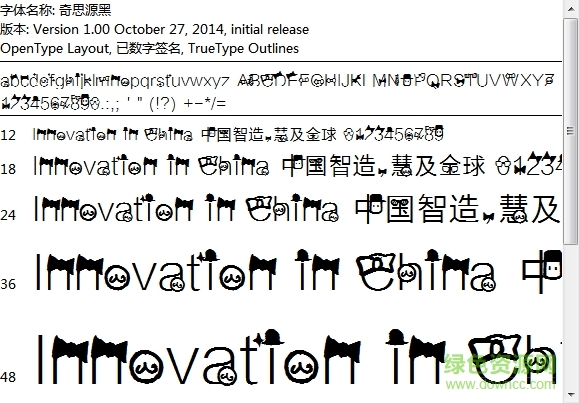
奇思源黑紳士作派體
紳士做派字體是奇思源黑推出的一款藝術(shù)字體,有著可愛(ài)的裝飾點(diǎn)綴,給文字增添獨(dú)特的趣味呈現(xiàn),顯得十分生動(dòng)活潑起來(lái),喜歡的朋友可以來(lái)綠色資源網(wǎng)收藏哦!
奇思源黑紳士作派體特色
紳士做派字體有著各種蝴蝶結(jié)、紳士帽、小胡子、四角星點(diǎn)綴,給文字增添了一股活潑之氣,讓你的設(shè)計(jì)更有青春活力的氣息。